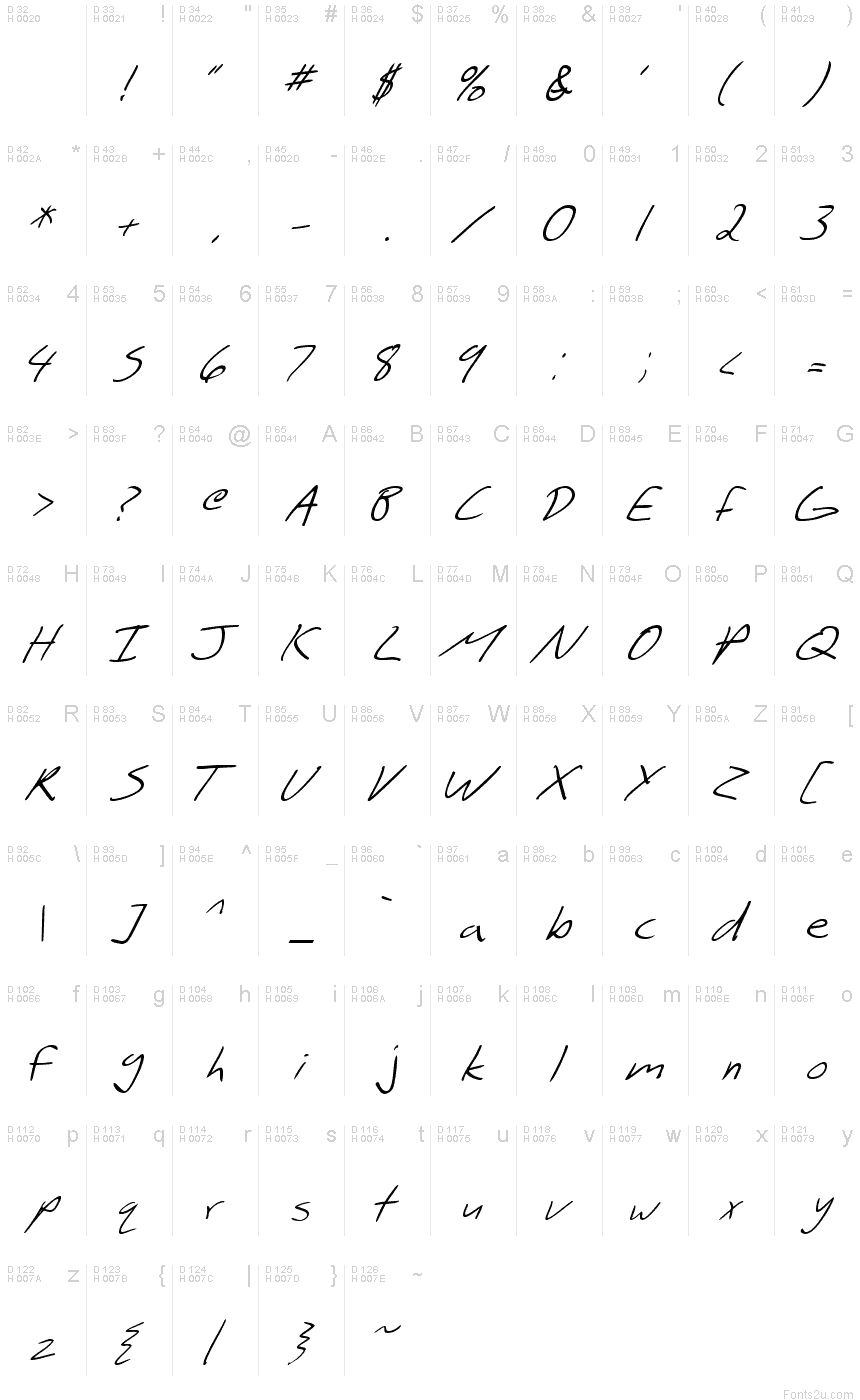
SF Scribbled Sans Italic od ShyFoundry to darmowy, odręczny font, który oddaje charakter szybkich notatek pisanych markerem. Litery pochylają się do przodu, łącząc długie, lekkie krzywe z nieco niespokojną linią, co nadaje całości luźny, szkicowy i nieco niecierpliwy wyraz.
Świetnie sprawdzi się na nagłówkach plakatów, ulotkach muzycznych, w brandingu w stylu notesu, na okładkach zinów czy kartach tytułowych – wszędzie tam, gdzie darmowy font ma być bezpośredni, a nie wygładzony. Krótkie hasła wyglądają w nim szczególnie dobrze, ponieważ płynne łączenia i otwarte pętle nadają słowom dynamikę szybkiego autografu.
SF Scribbled Sans
ShyFoundry
Derek Vogelpohl